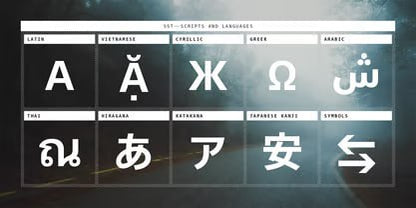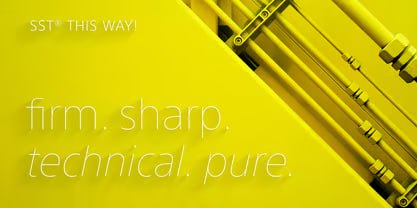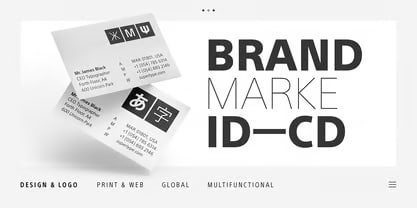
SST Font Family - Firm, Sharp, Technical & Pure
La famille SST marie harmonieusement une lisibilité naturelle et une structure moderne et épurée. Cette alliance crée une police à la fois discrète et polyvalente, qui s'adapte à toutes vos applications typographiques. Qu'il s'agisse de titres imposants pour l'impression ou de textes miniatures pour des emballages, son style reste intemporel et convivial.
Des options pour toutes vos créations
Pour répondre à l'ensemble de vos besoins, la SST propose un large éventail d'options :
Six graisses différentes, de l'ultra léger au lourd.
Un jeu de caractères W1G complet.
Des versions italiques pour chaque graisse.
Trois designs condensés pour les espaces restreints.
Deux caractères monospaces pour un look machine à écrire.
Une conception pensée pour le monde
Initialement créée pour la marque mondiale Sony, la SST est le fruit d'une collaboration avec un réseau de designers locaux à travers le monde. Cette approche garantit une cohérence parfaite entre les différentes langues, du latin au grec, en passant par le cyrillique et de nombreuses langues asiatiques. Les détails subtils de la police, comme la courbure ou la largeur du trait, sont ainsi préservés et uniformes, assurant une image de marque forte et unifiée à l'échelle internationale.